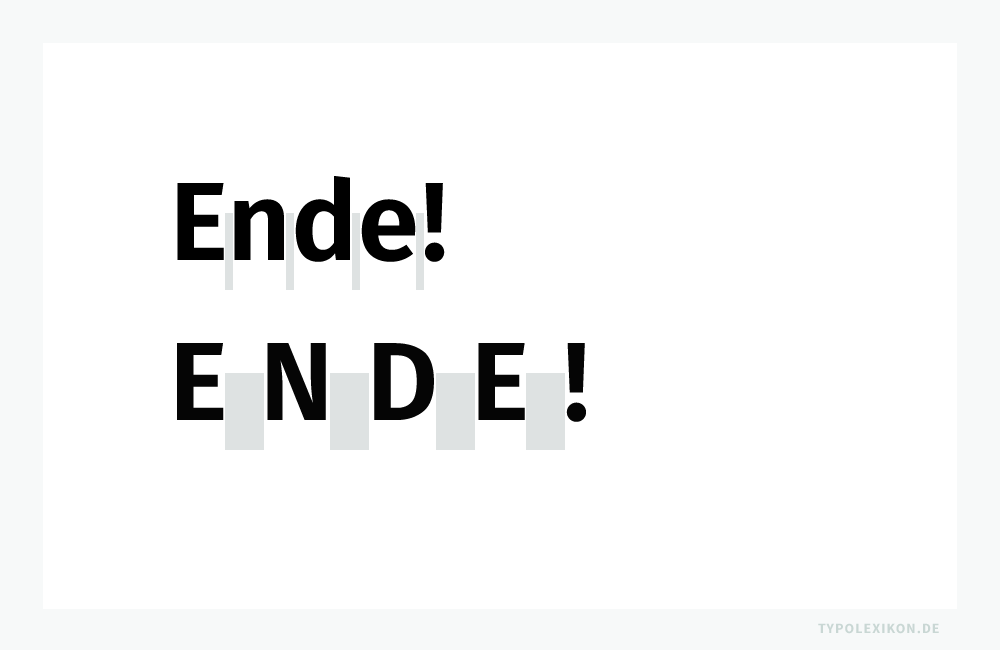
Zeichenabstand bei Ausrufezeichen
Im deutschen Schriftsatz wird im glatten Satz weder ein Leerraumzeichen noch ein Teilgeviert zwischen dem letzten Buchstaben und dem Ausrufezeichen eingefügt. Bei einer erweiterten Schriftlaufweite (LW+) wird der Wortzwischenraum durch das im OpenType-Font hinterlegte Kerning automatisch angepasst.